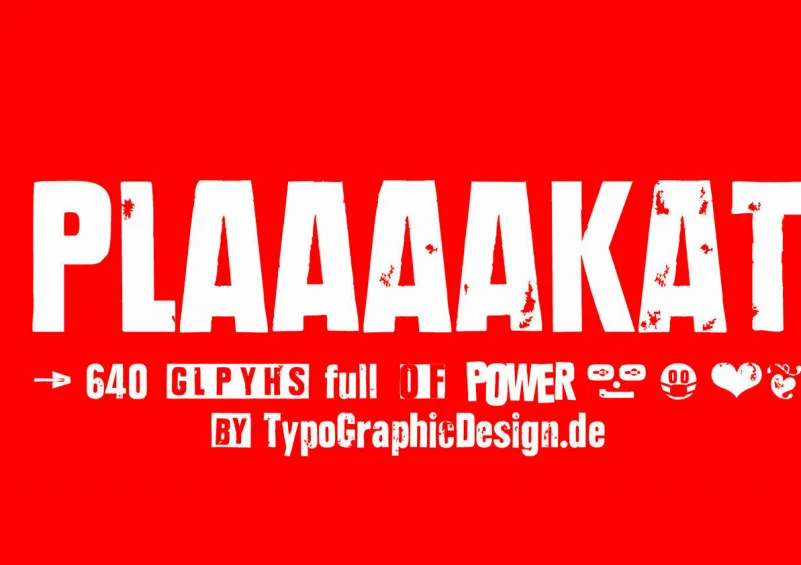
Estamos muito felizes por você ter olhado para esta fonte moderna. Trata-se de uma sans serif ideal para quem busca a liberdade criativa. A fonte foi projetada em 2021 pela Typo Graphic Design, um lugar incrivelmente especializado na criação de fonts. Sua inspiração vem da origem do tipo Wood Letter de Paul Renners e seu estilo inovador está disponível para uso nos logos, revistas, cartazes, publicidade além de ser ótima para headlines em sites. A fonte “PLAKAT” foi pensada para a sua liberdade criativa. Seu design vem do Plak Schmalfette da Paul Renners typeface e é inspirado tanto no passado quanto no presente. Ela oferece uma grande liberdade de utilização, sendo perfeitamente adequada para uso em tamanho maior como headline. Esta fonte “PLAKAT” Wood Font Family seria um ótimo escolha para a criação de logotipos, revistas, cartazes ou publicidade, e até mesmo para headlines no seu site web. Ela traz ao seu projeto uma personalização única que vai destacar sua marca.